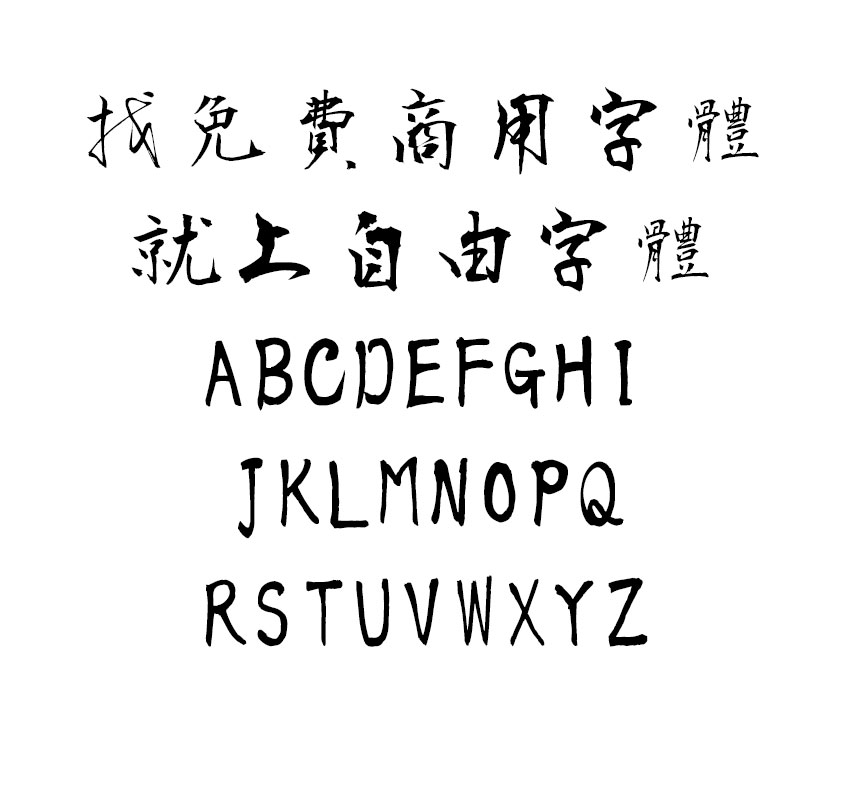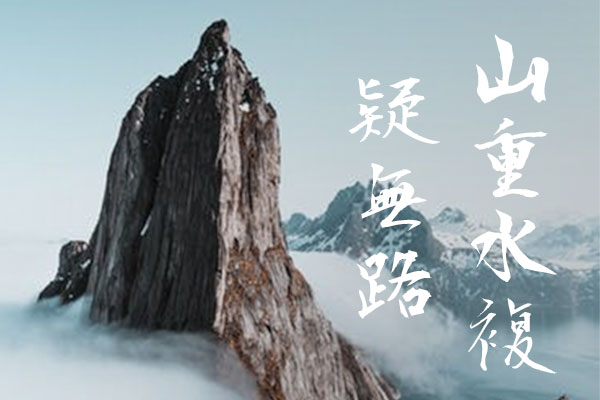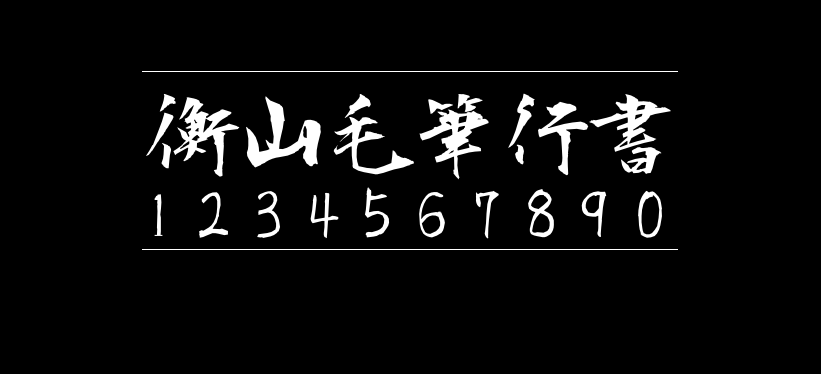
衡山毛笔行书
衡山毛笔行书( 衡山毛筆フォント行書 / KouzanBrushFontGyousyo)是日本书法家青柳衡山先生挥毫写成的毛笔字体,这款字体行笔潇洒飘逸,特别适合海报标题的字体。这款字体包含JIS第1水准2965字,第2水准3390字。
由于字体采用的日本的JIS标准,所以支持的简体字数不算多,但是繁体却是比较齐全的。不过目前国内可以免费商用的毛笔字体选择比较有限,中国大陆的有庞门正道粗书体、演示秋鸿楷、演示夏行楷、演示春风楷、鸿雷板书简体这几款。如果喜欢衡山毛笔行书这款字体,就赶紧下载试试吧!